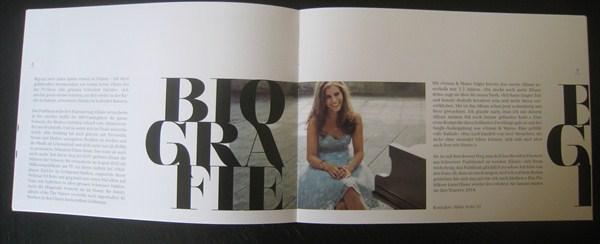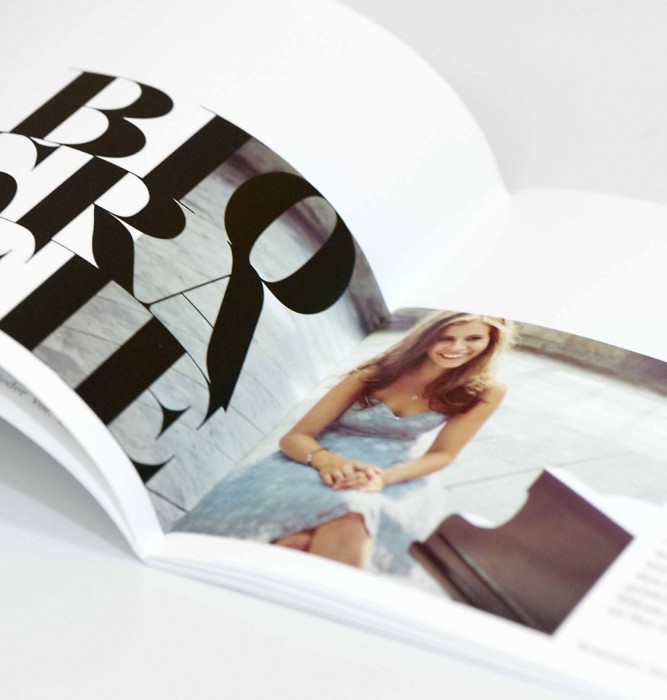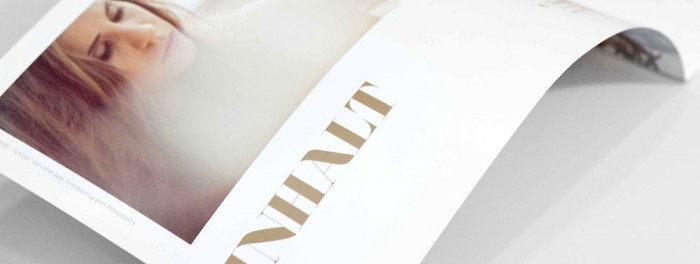
klassizistische Schrift
Habe kürzliche diese schöne klassizistische Schrift entdeckt und würde gerne wissen,
ob kemand von euch diese kennt?
Auffällig ist jeweils der Stamm beim «A» und «N».
Wenn du uns verrätst, woher das stammt, könnte man der Einfachheit halber ein pdf des Verlags/Magazins suchen und dort nachschauen …